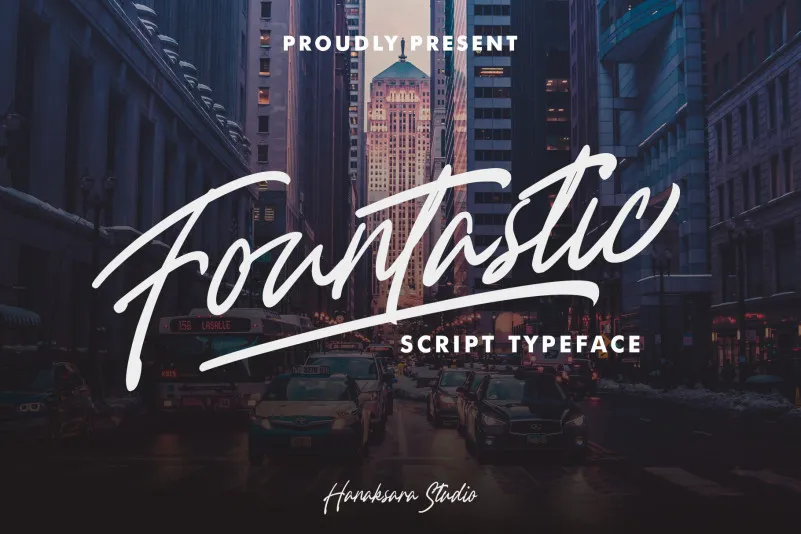
Fountastic Script Font – Download Grátis
A Fountastic Script é uma nova adição à família das fontes Hanaksara.Studio, introduzindo um estilo casual e moderno que traz a praticidade do desenho manual aos seus projetos digitais. Com linhas leves e gráficos minimalistas, esta fonte se destaca por seu design cuidadosamente elaborado a mão, criando uma aparência quase autêntica da escrita de mão ou letra contínua. Fountastic Script é perfeita para quem busca um estilo elegante e moderno para criar letras customizadas, sem precisar recorrer à manualidade. Ela não apenas facilita a criação de letras personalizadas com uma fonte, mas também oferece uma variedade de opções de design que podem ser usadas em diversos contextos digitais, da mídia social aos relatórios profissionais. Em conjunto, estas características tornam Fountastic Script uma escolha inconfundível para quem busca um estilo único e versátil no seu trabalho digital.